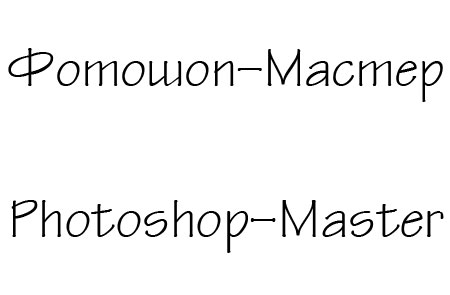
Дополнения Шрифты Татьяна Гапонова 12 июля 2009 Шрифт - TECHNICAL Di Интересный шрифт с поддержкой русского языка. Скачать Шрифт - TECHNICAL Di
Четкий)
симпатичный
Сойдёт
Как аккуратно!